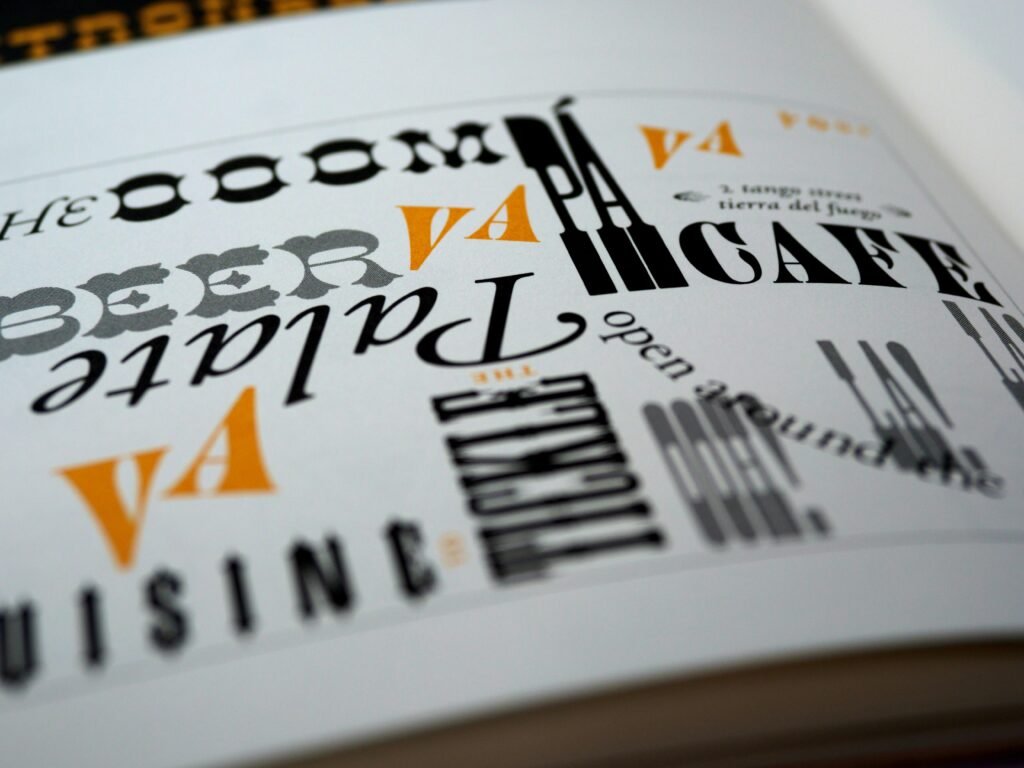
Typography: So wird Schrift zum Marketing-Motor
Deine Website sieht aus wie ein Designpreisgewinner – aber niemand liest, niemand klickt, niemand bleibt? Dann liegt’s vielleicht nicht am Content, nicht am Funnel und auch nicht an deinem SEO. Es liegt an der Schrift. Ja, richtig gelesen: an der Typografie. Denn Schrift ist nicht nur Form. Sie ist Funktion. Sie ist Psychologie. Und sie ist knallhartes Marketing – wenn man weiß, was man tut.
• Warum Typografie in Online-Marketing kein Deko-Thema ist, sondern ein Performance-Treiber
• Wie Schriftwahl Bounce Rates killen oder Conversions pushen kann
• Die wichtigsten Typografie-Kriterien für UX, SEO und Brand Identity
• Welche Schriftarten du besser nie auf einer Website einsetzt – und warum
• Wie du mit Webfonts, FOUT und FOIT technisch sauber arbeitest
• Die Rolle von Responsive Typography im Mobile-First-Zeitalter
• Core Web Vitals und Typografie: Wie Fonts deine Ladezeiten ruinieren können
• Ein Leitfaden für professionelle, marketingwirksame Typografie-Optimierung
Typografie ist kein Design-Gimmick. Sie ist der unsichtbare Dirigent deiner User Experience. Und sie entscheidet, ob dein Content gelesen wird – oder weggeklickt. In der Welt des Online-Marketings, wo Millisekunden entscheiden und Aufmerksamkeit die härteste Währung ist, kann eine falsche Schriftwahl deinen ROI pulverisieren. In diesem Artikel erfährst du, warum Schrift mehr ist als Stil – und wie du sie in einen echten Marketing-Motor verwandelst.
Warum Typografie im Online-Marketing ein echter Conversion-Faktor ist
Typografie ist die Schnittstelle zwischen Inhalt und Nutzer. Sie beeinflusst, wie Inhalte wahrgenommen, verstanden und verarbeitet werden. Und damit ist sie ein direkter Performance-Faktor – nicht nur im UX-Design, sondern auch im SEO, in der Conversion-Optimierung und sogar im Branding.
Wenn User nicht lesen können – weil die Schrift zu klein, zu dünn oder schlicht unleserlich ist – verlassen sie die Seite. Punkt. Eine schlechte Lesbarkeit erhöht die Bounce Rate, senkt die Verweildauer und killt jede Conversion-Strategie. Und das Beste? Viele merken nicht einmal, dass die Typografie der stille Killer ist.
Gute Typografie hingegen führt den Blick, strukturiert Inhalte, schafft Vertrauen und transportiert Markenwerte. Sie macht Texte nicht nur lesbar, sondern erlebbar. Und das wirkt sich direkt auf die Performance deiner digitalen Kanäle aus. Studien zeigen: Schon kleine typografische Anpassungen können CTRs um bis zu 30 % steigern. Kein Witz.
In Zeiten von Mobile-First und Core Web Vitals wird typografische Exzellenz sogar technisch relevant. Fonts beeinflussen Ladegeschwindigkeit, Layout-Stabilität und User Experience – alles Faktoren, die Google heute messbar bewertet. Wer hier schlampt, verliert nicht nur Leser, sondern auch Rankings.
Fazit: Typografie ist keine Geschmacksfrage. Sie ist ein strategisches Asset. Wer sie beherrscht, gewinnt. Wer sie ignoriert, verliert – Sichtbarkeit, Kunden und Umsatz.
Die wichtigsten typografischen Kriterien für Usability, SEO und Branding
Typografie ist mehrdimensional. Sie beeinflusst nicht nur das visuelle Erscheinungsbild, sondern auch die Nutzerführung, die Informationsarchitektur und die Performance deiner Website. Deshalb braucht sie klare Kriterien – nicht nur für Designer, sondern für jeden, der mit Digitalmarketing ernst macht.
• Lesbarkeit (Readability): Die Basis jeder typografischen Entscheidung. Zu kleine Schriftgrößen, zu geringe Kontraste oder enge Zeilenabstände machen Texte unlesbar – besonders auf mobilen Geräten.
• Hierarchie: Gute Typografie strukturiert Inhalte. Headline, Subheadline, Fließtext, Call-to-Action – alles braucht eine klar definierte visuelle Ordnung, die den User intuitiv führt.
• Kohärenz: Einheitlichkeit im Schriftsystem schafft Vertrauen und Professionalität. Wer fünf verschiedene Fonts auf einer Landingpage nutzt, wirkt wie ein Hobby-Blogger von 2006.
• Markenidentität: Schrift transportiert Tonalität. Ob seriös, verspielt, modern oder edel – der Font ist Teil deiner Marken-DNA. Die falsche Schrift schadet deinem Branding mehr als ein schlechtes Logo.
• Technische Performance: Fonts beeinflussen Ladezeiten, Layout-Stabilität (CLS) und Time-to-Interactive. Besonders Webfonts müssen sauber eingebunden und gecacht werden, sonst leidet die gesamte UX.
Diese Kriterien sind nicht optional. Sie sind Pflicht. Und sie gelten nicht nur für Text-lastige Seiten, sondern auch für E-Commerce, SaaS-Landingpages und jedes andere digitale Produkt, das mit Sprache arbeitet. Also: immer.
Webfonts, Performance und SEO: Die unsichtbare Gefahr schlechter Font-Implementierung
Webfonts sind der feuchte Traum jedes Designers – und der Albtraum jedes Performance-Engineers. Denn falsch eingebundene Webfonts sind einer der häufigsten Gründe für schlechte Ladezeiten, Layout-Shifts und mieses SEO. Willkommen in der Welt von FOUT, FOIT und CLS.